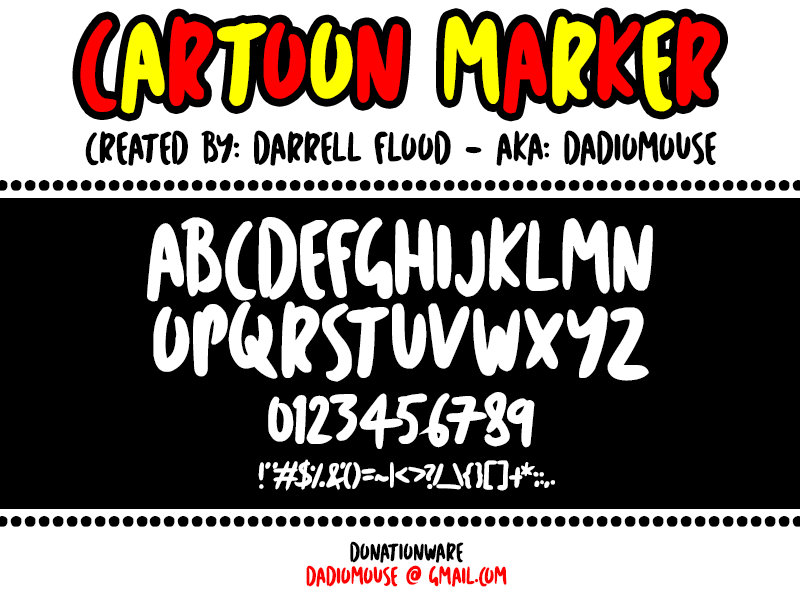
Esta fonte, criada pelo designer Darrell Flood usando a High Logic Scanahand, é uma opção perfeita para quem busca adicionar um toque leve e divertido a seus trabalhos digitais. (E mesmo que eu ainda valorize qualquer doação de você, independente!) Esta font é gratuita para uso pessoal e pode ser incorporada em projetos pessoais sem preocupações legais. Darrell Flood, um criativo talentoso, usou seu conhecimento avançado de High Logic Scanahand para desenvolver uma família de caracteres cheia de vida que se adaptará perfeitamente aos esboços infantis ou a qualquer tipo de projeto infanto-juvenil. Seja você designer gráfico, ilustrador ou até mesmo o criador de conteúdo digital em constante movimento, esta font é um excelente complemento para sua biblioteca de recursos. Para aqueles que buscam uma alternativa mais leve e divertida à fontes tradicionais, a High Logic Scanahand representa um ótimo ponto de partida. Suas linhas suaves, formas curvilíneas e cores vibrantes criam um ambiente acolhedor para qualquer projeto em que seja aplicada. Este é um verdadeiro complemento perfeito para qualquer designer em busca de uma fonte divertida e versátil.